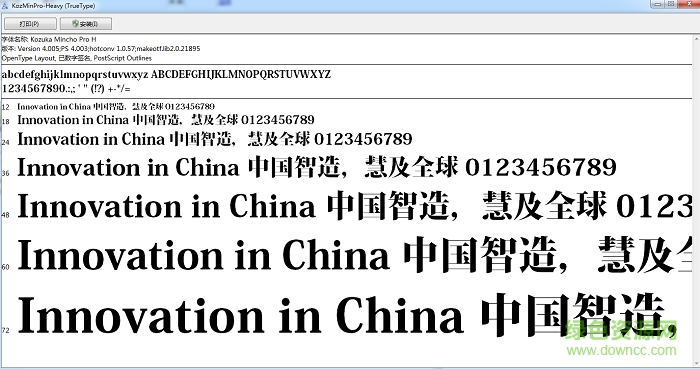
kozuka mincho pro h字体是一款较粗的小塚明朝字体,也就是宋体字体,典雅工整,笔法挺劲,印小字也清晰易读,需要的小伙伴快来绿色资源网下载吧!
【秀丽体】
也是把宋体字形的笔划修正而成。字体庄重端正,是最受欢迎的字体之一。
【线条体】
以前称为「黑体」或「方头」。字体粗壮、厚实、醒目。字的笔划粗幼,横直相等。多用于标题制作,有强调的效果,线条较幼的也可以用来排正文。
【楷书体】
就是用毛笔很工整地「手写」的字体,笔触柔和悦目,常用于排标题、课本、请柬等。